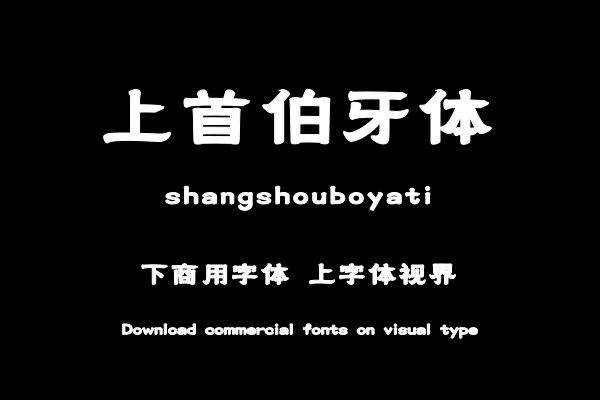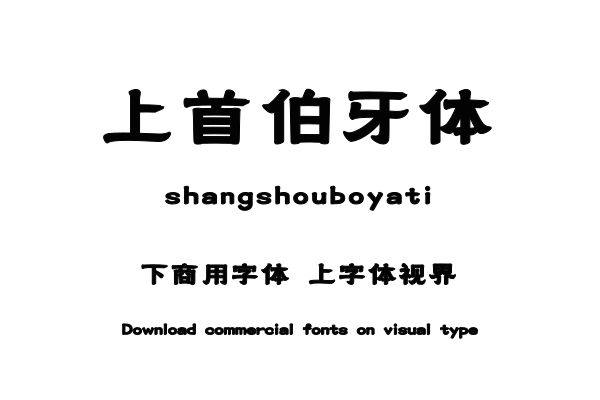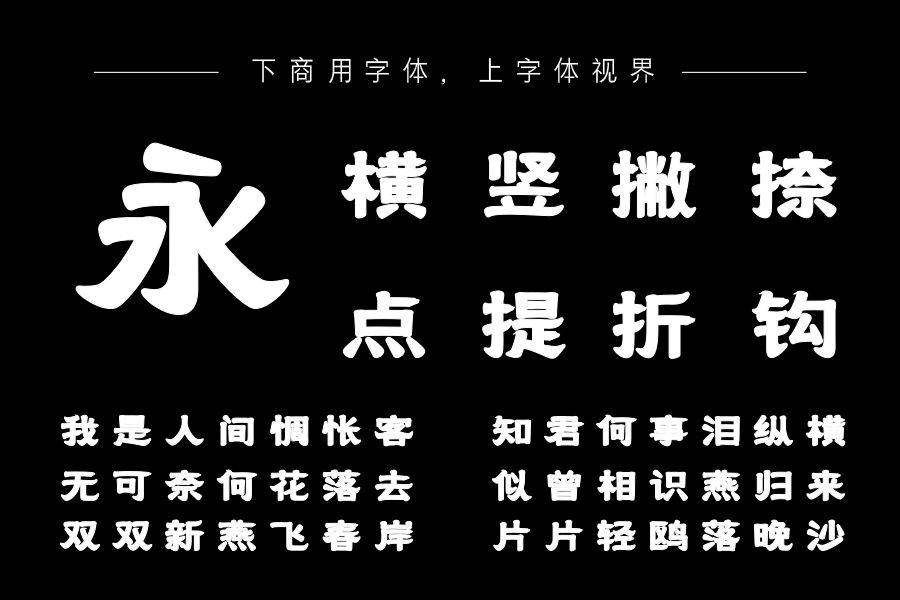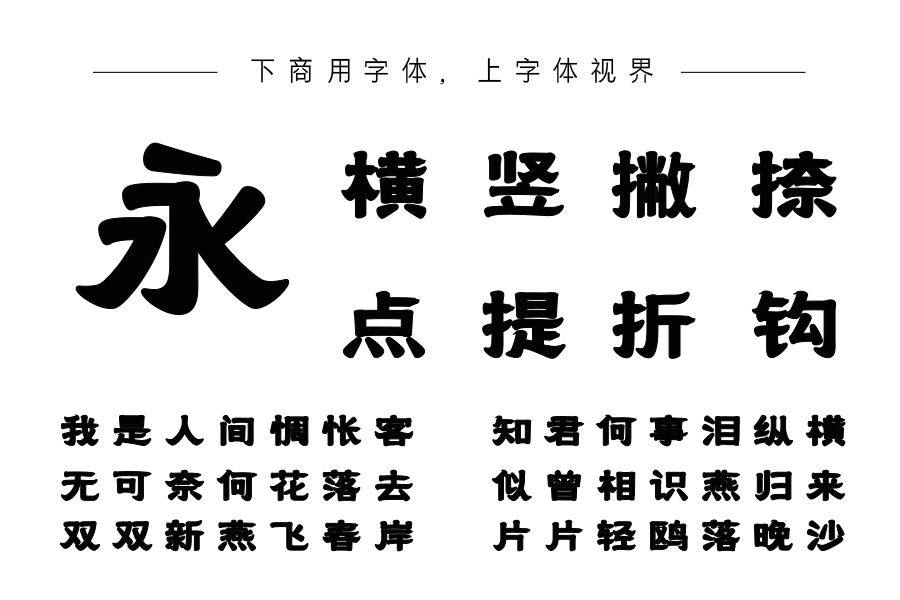
上首伯牙体,是一种具有高雅、清逸、知音难觅等文化内涵的一款字体。具有特定韵味或意境字体风格。它不仅仅是一种字体设计,更是一种情感的表达和精神的象征。购买须知:“下载服务费”与“字体VIP”所获得字体 仅用于个人非商用, 商用请联系付费授权。本字体为电脑用字,手机没有root权限不支持直接手机换字(手机如何root,请自行百度搜索教程)。购买前请先 了解清楚后再付款 ,字体为虚拟产品无法回收 一旦购买不支持退款。